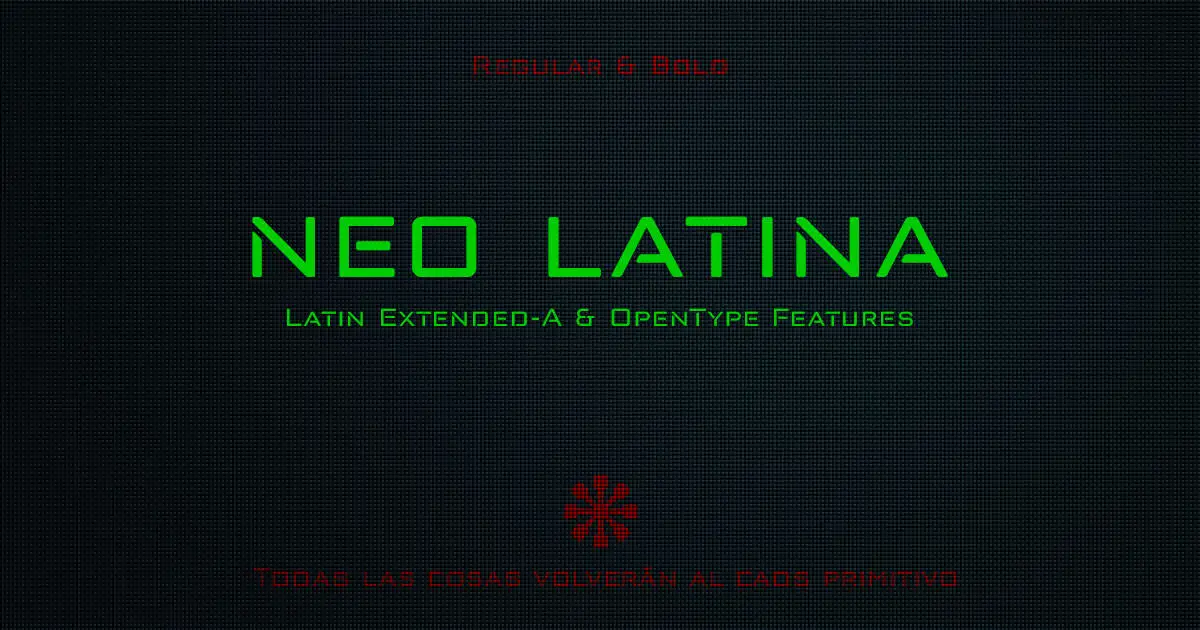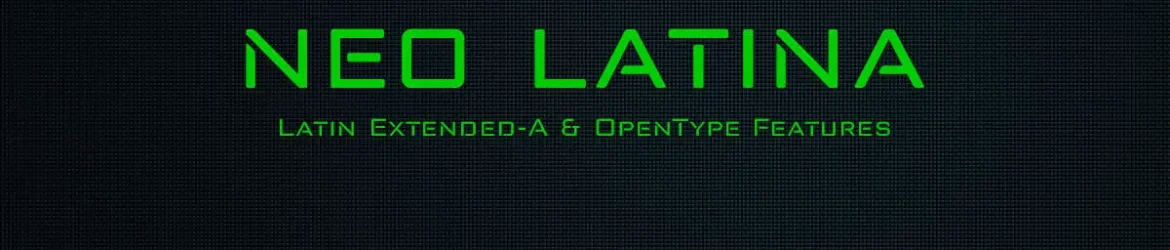
Neo Latina é uma elegante fonte de linhas gerais, ideal para design gráfico moderno e futurista. Suas linhas retangulares e caracteres quadrados, com terminações arredondadas nos bordões, conferem ao tipo um aspecto sci-fi único. Inspirada nas tipografias geométricas dos anos 20 do século passado, Neo Latina é uma herdeira legítima desses estilos, modernizada para atender às necessidades de design digital atual, seja em tela ou impressão. Suas linhas clean e versáteis permitem sua utilização em uma variedade de ambientes gráficos, incluindo anúncios publicitários, jogos digitais, títulos de filmes, logotipos e design editorial. Um dos pontos mais interessantes é a inclusão da moeda Bitcoin no seu leque, representada por um símbolo ligado com a combinação b# (ligaturas), proporcionando uma personalidade ainda maior para sua utilização. Esta fonte vem em duas variantes principais: Regular e Bold, oferecendo designistas e designers comerciais uma ampla gama de opções para atender às necessidades específicas do projeto. Seja por seu design clean ou pela inclusão única da moeda Bitcoin, Neo Latina é uma escolha versátil para aqueles que buscam um tipo clássico mas moderno.